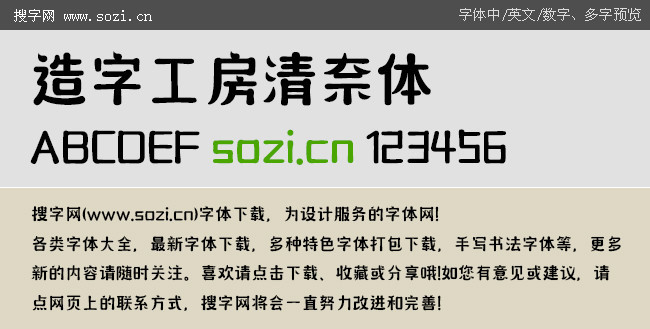
造字工房清奈體
搜字網(wǎng)給大家提供一款造字工房清奈體中文字體下載,造字工房清奈體字形方潤豐腴,筆意舒展充暢,宛轉(zhuǎn)流美,神氣充足,有極強(qiáng)的視覺表現(xiàn)力。適用于大標(biāo)題、包裝設(shè)計(jì)、海報(bào)設(shè)計(jì)等應(yīng)用。(本字體為個(gè)人非商用版,如需要商用請(qǐng)聯(lián)系官方購買版權(quán))